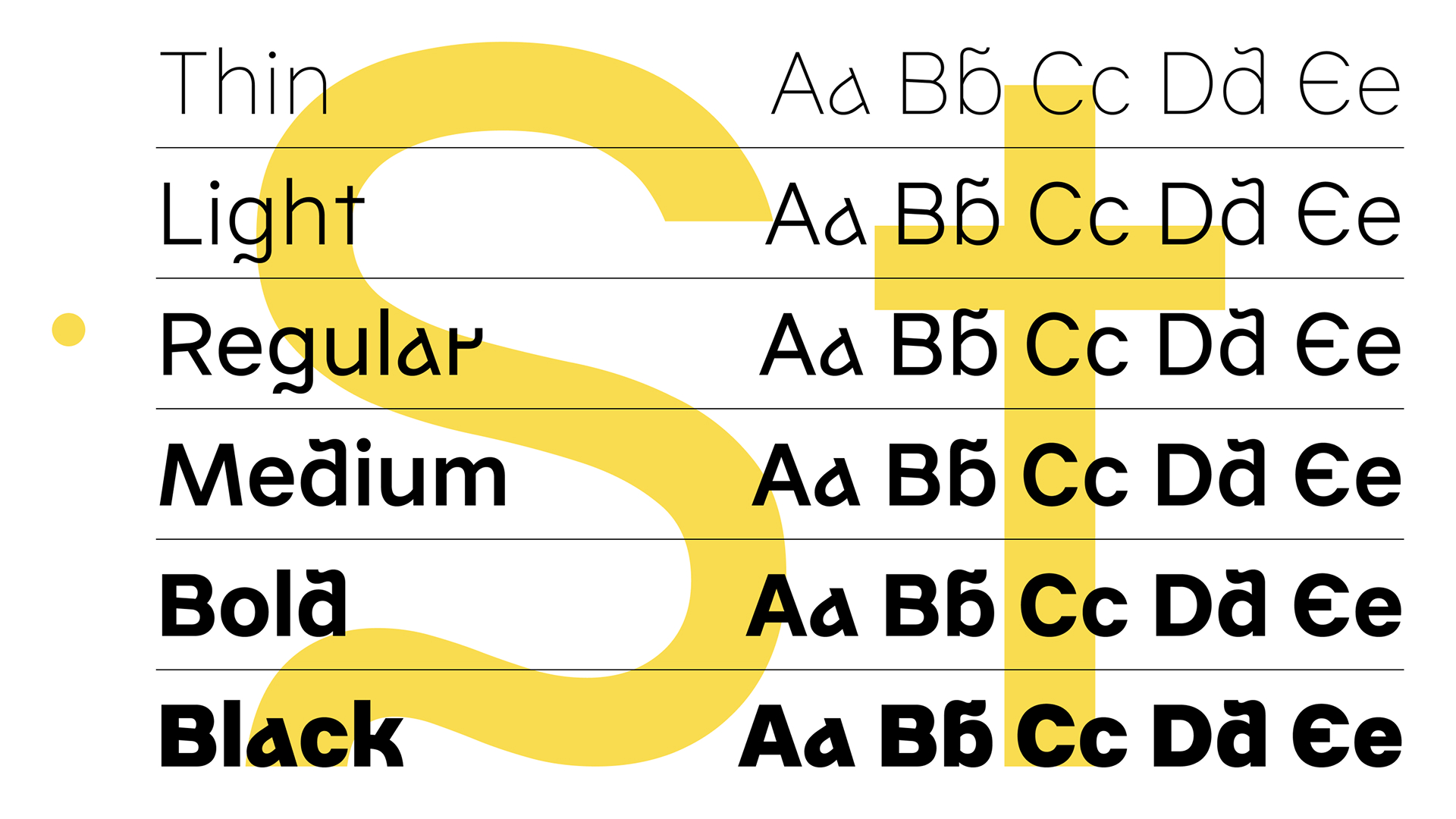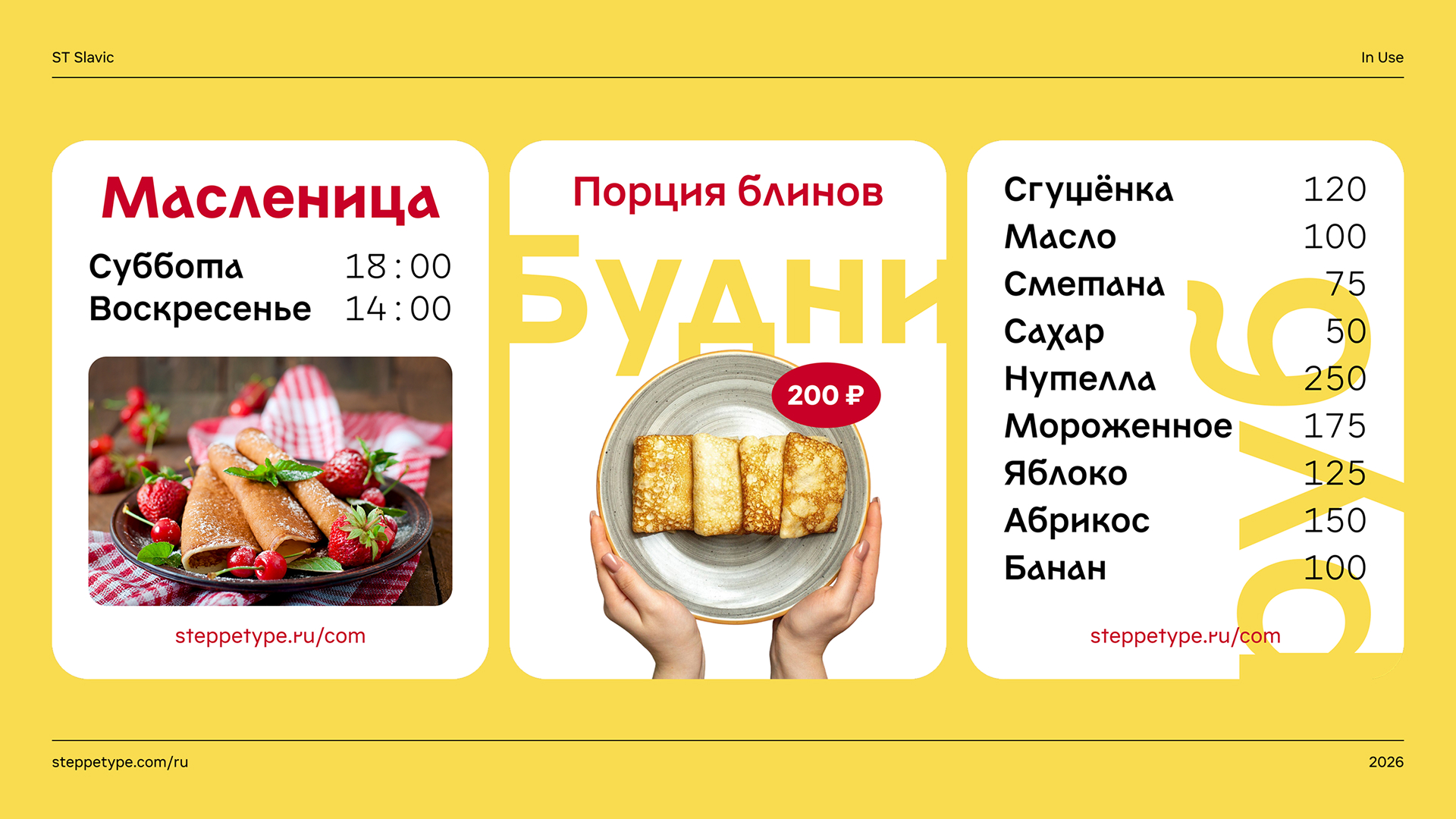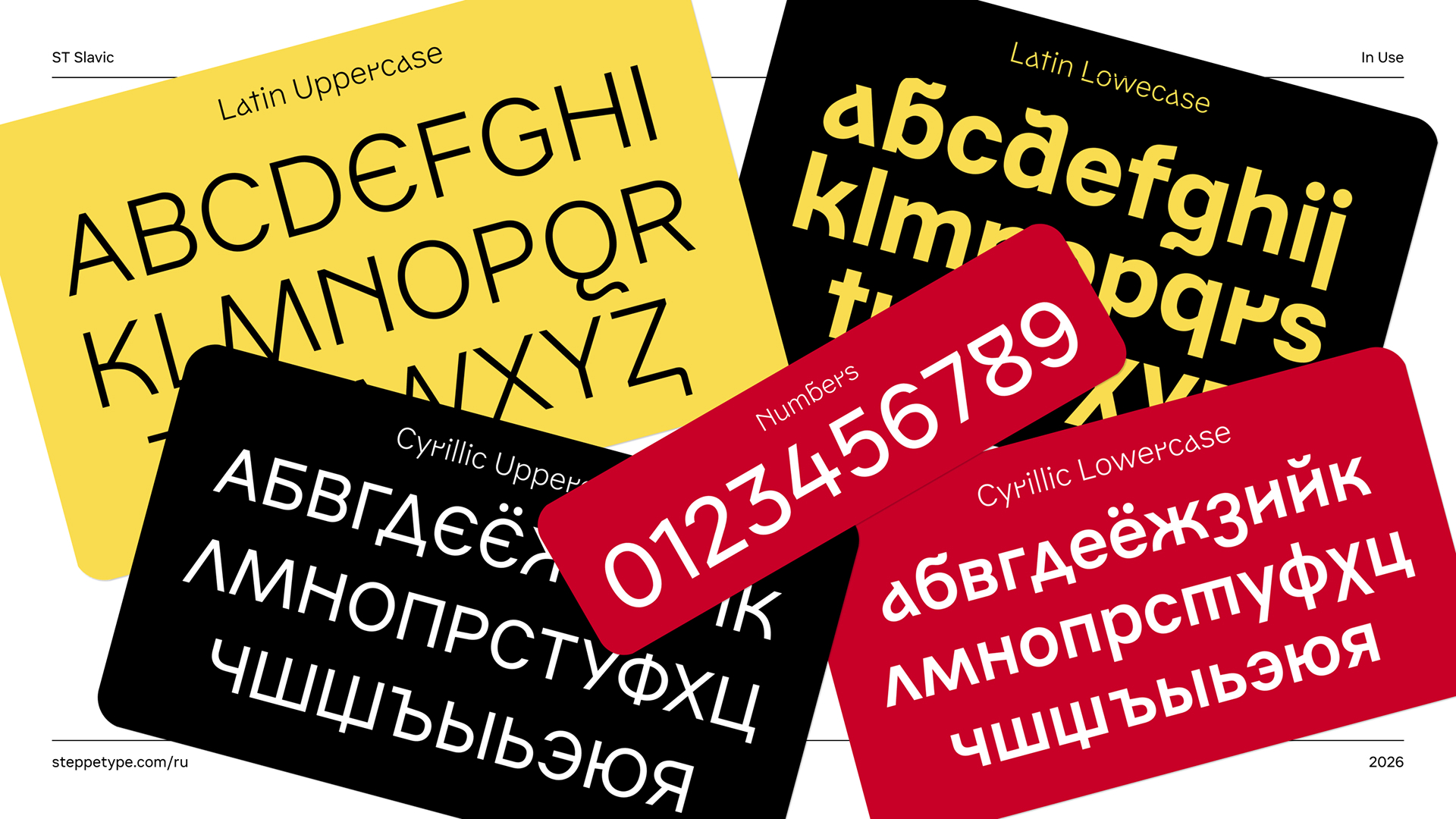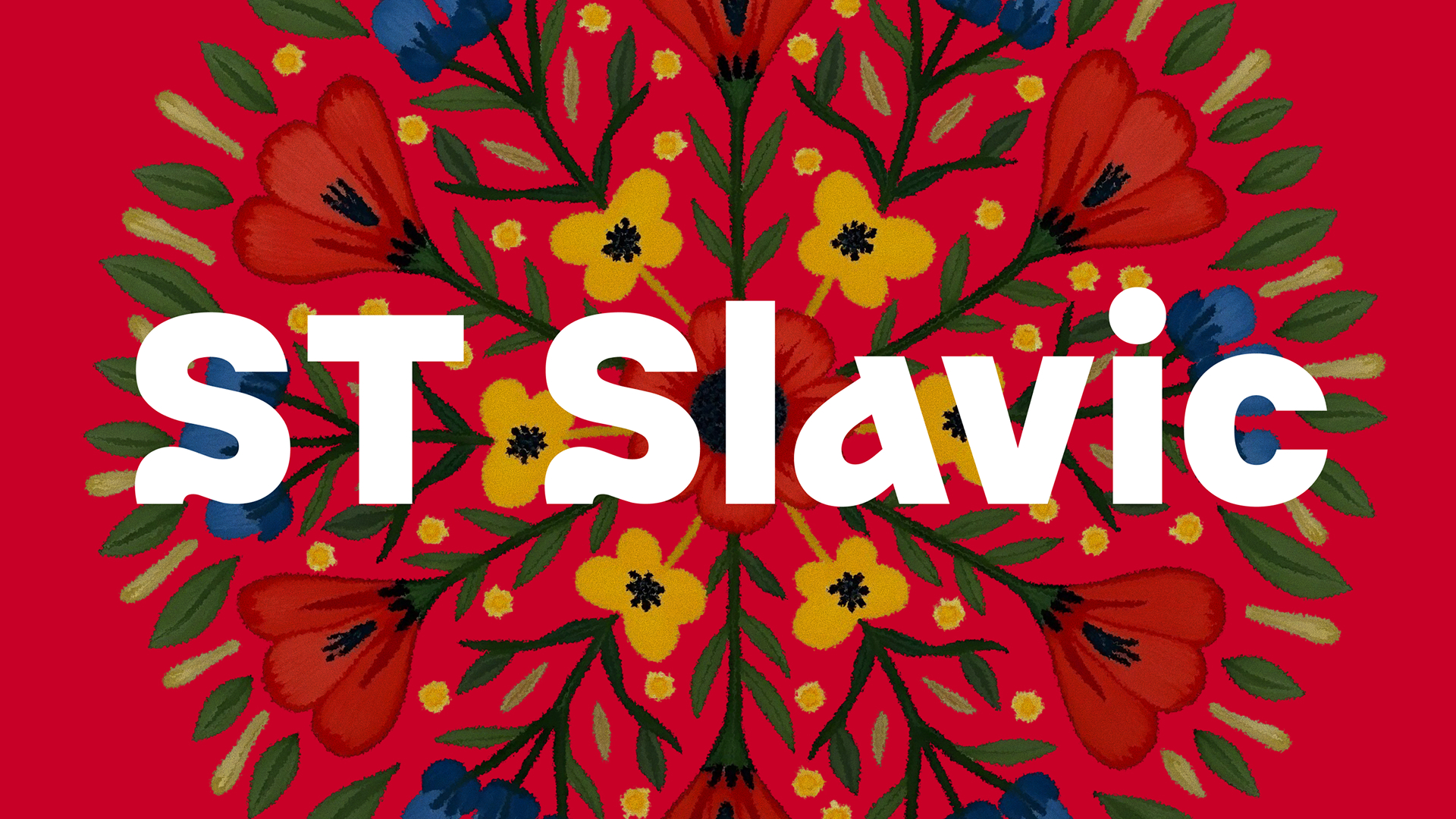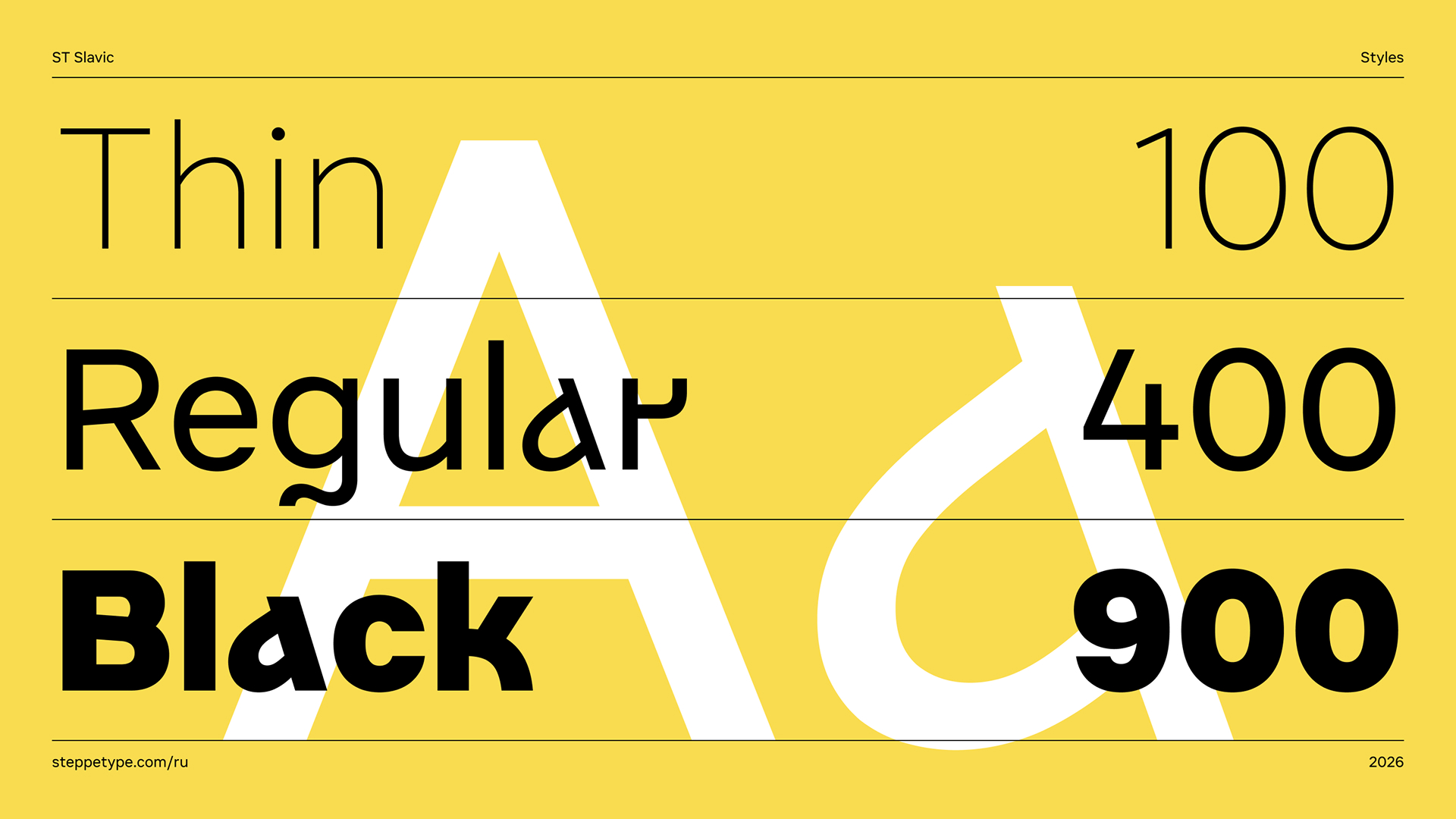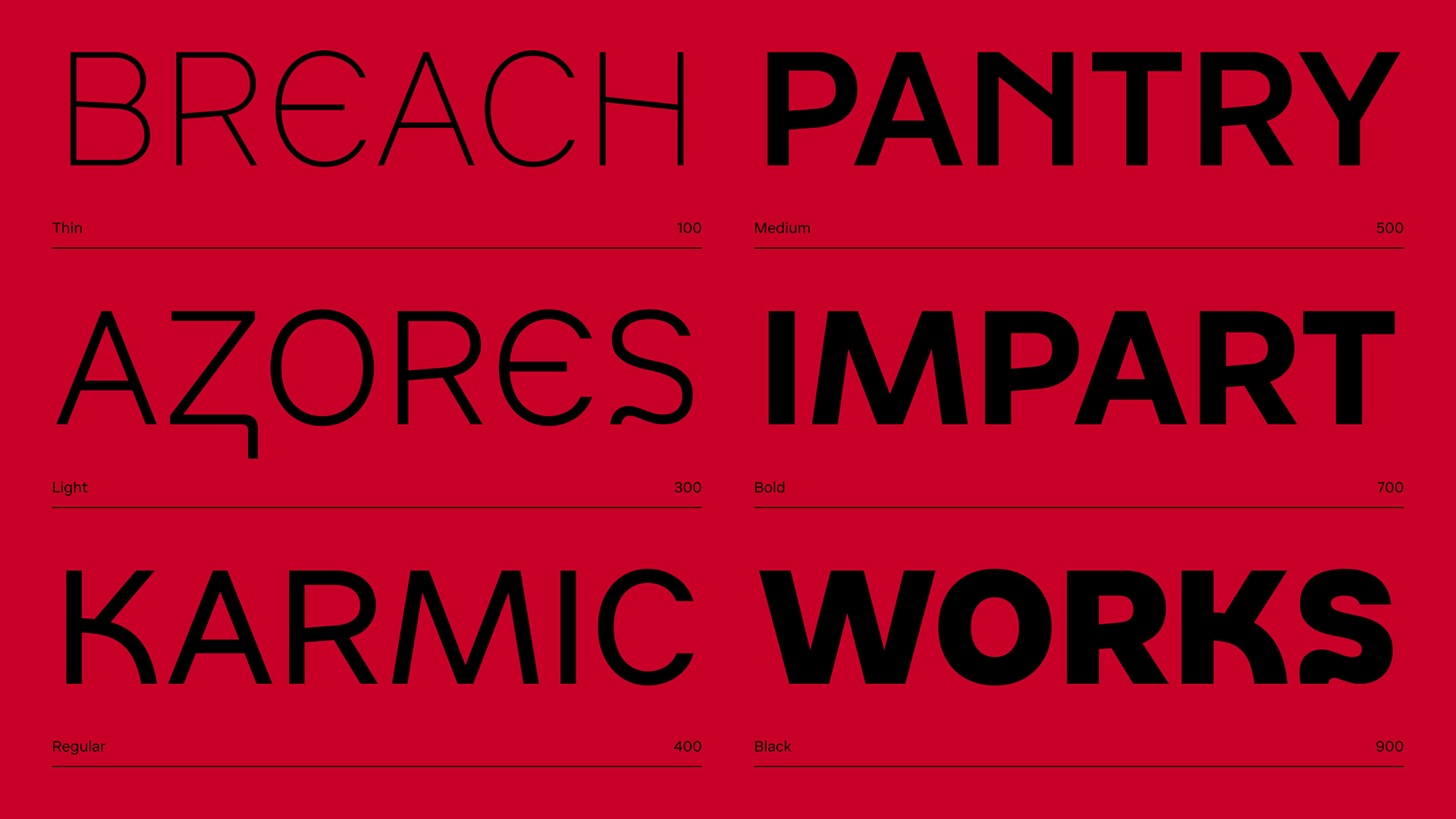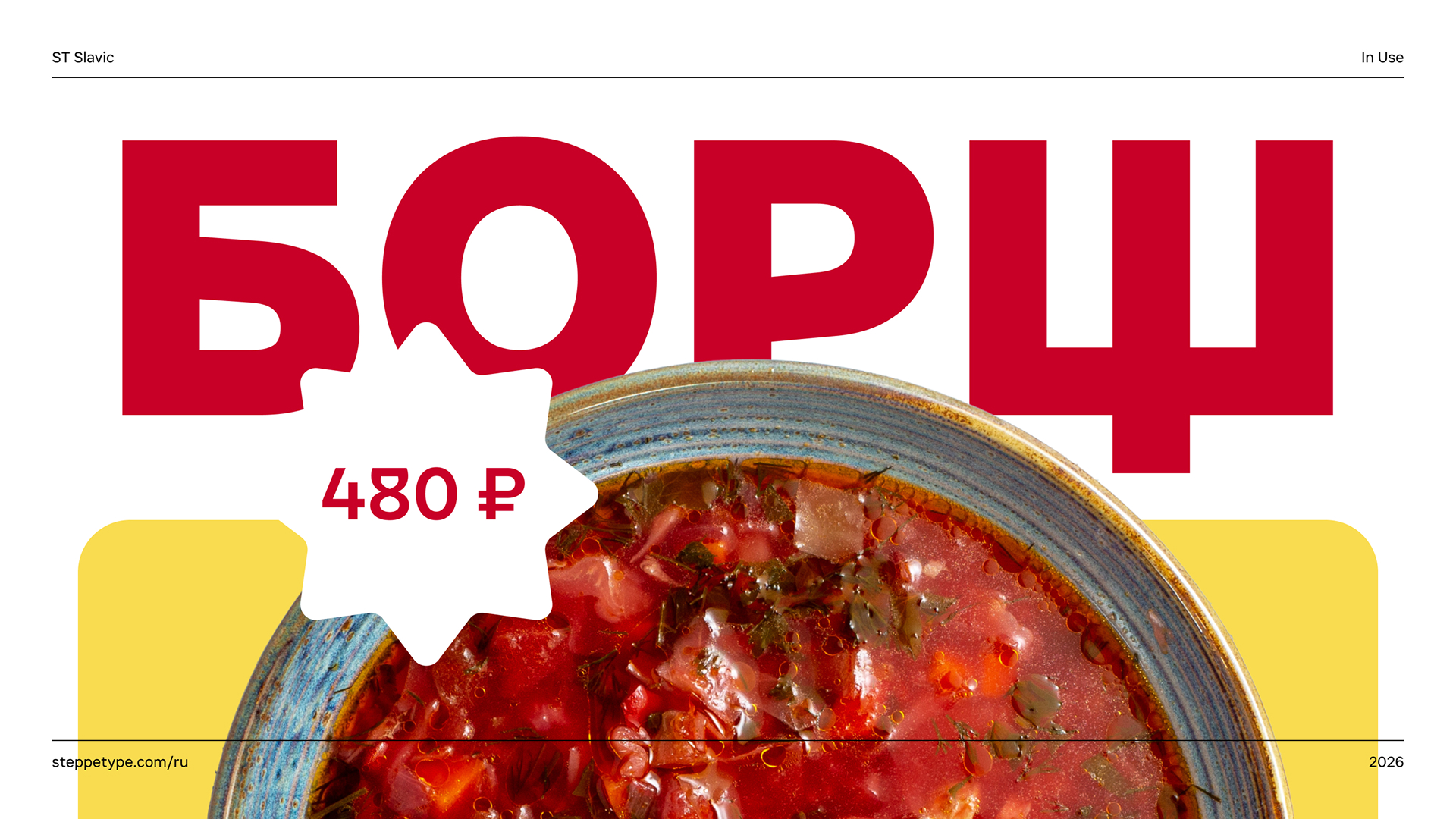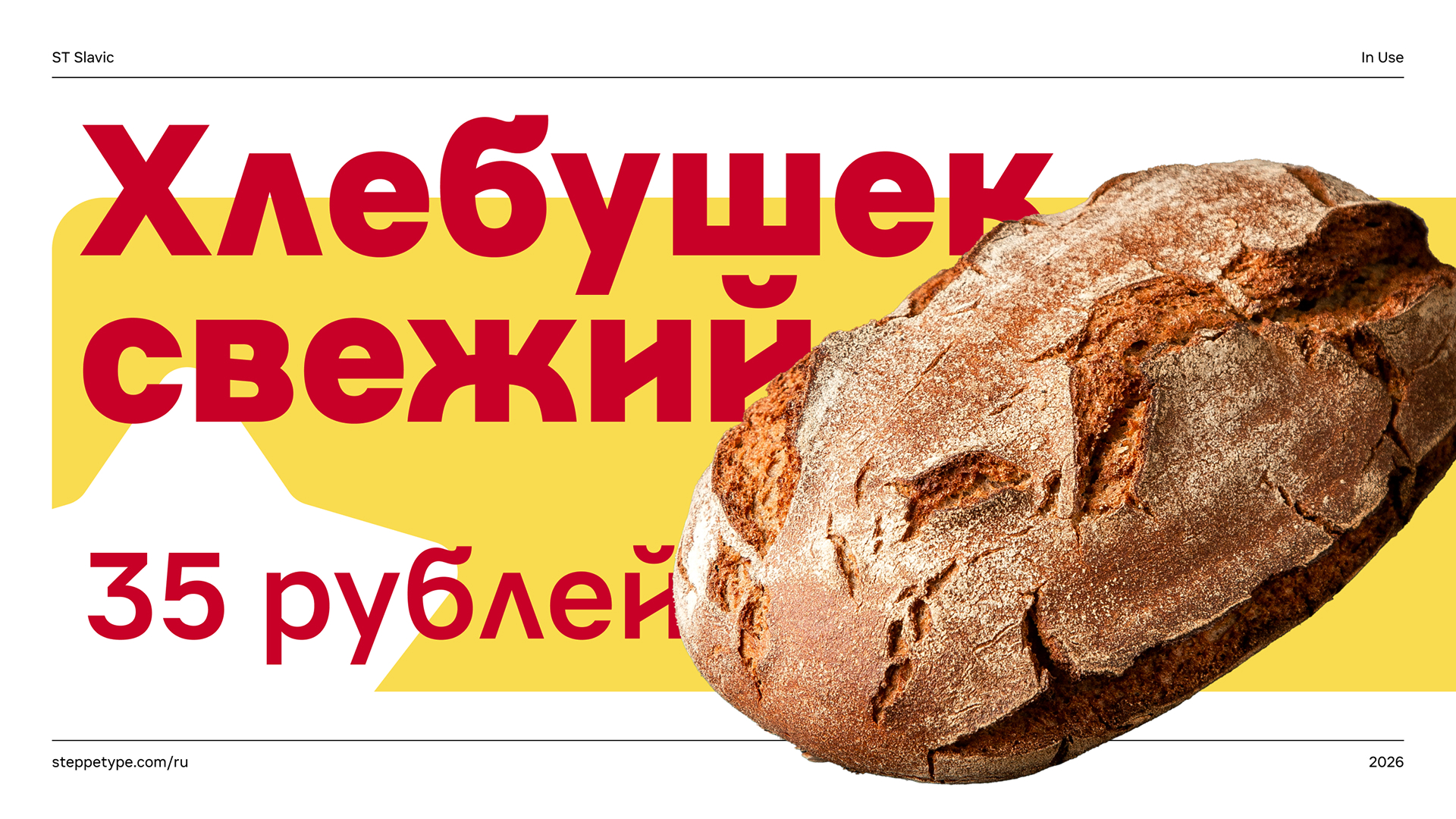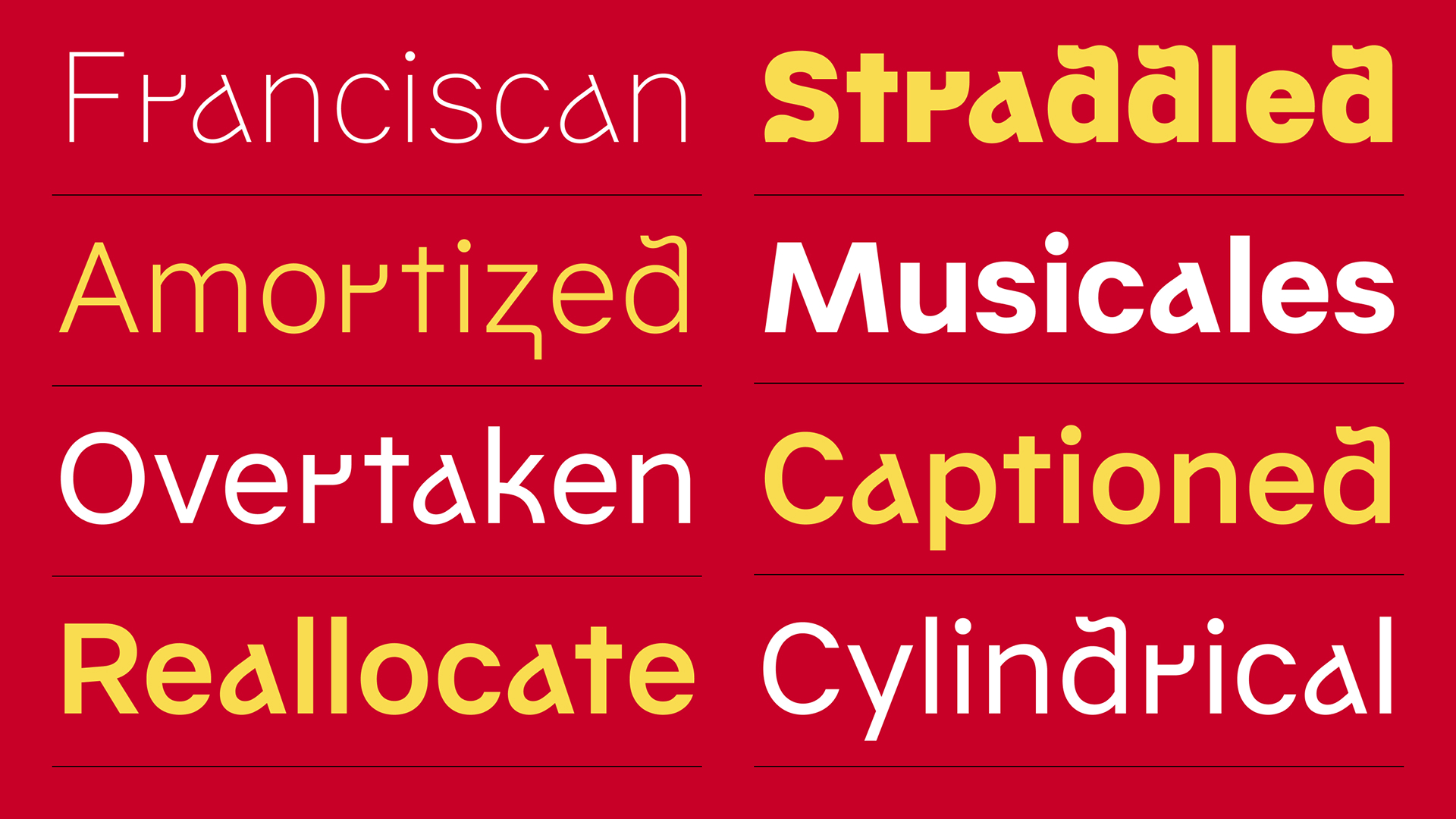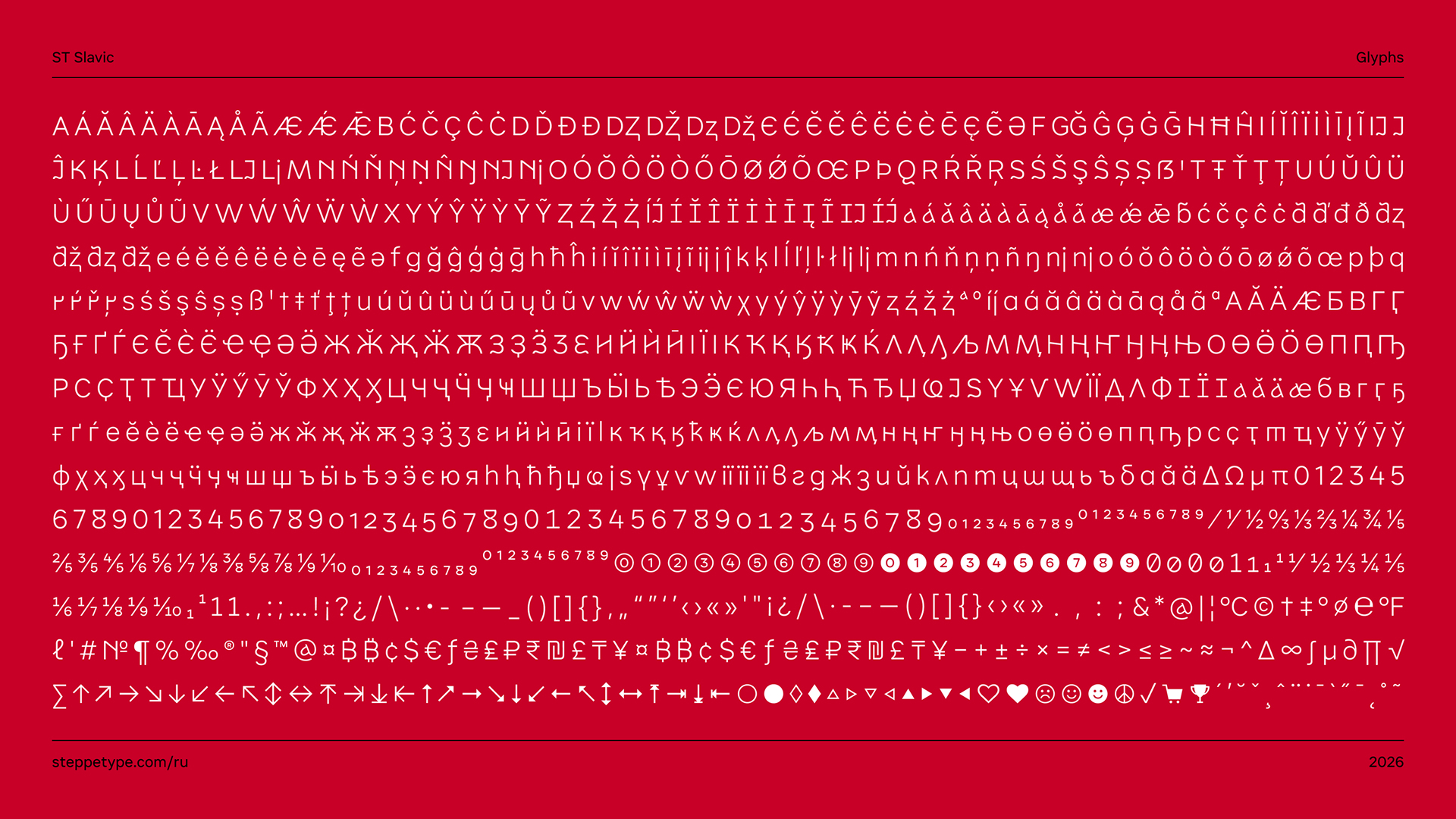
Экспериментальный шрифт
ST Slavic
Описание работы
Изначально планировалось создать большой стилистический сет для ST Sans. Но он оказался настолько большим, что было принято решение создать отдельное семейство под названием ST Slavic. Также был удачно подобран известный слоган под ход проекта: "Взболтать, но не смешивать". Он идеально подходит под первоначальную идею: внедрение старославянских форм кириллицы в современный неогротеск, не нарушая целостность основных графем. В итоге получился довольно универсальный шрифт с насыщенными славянским вкусом, включая набор латиницей.